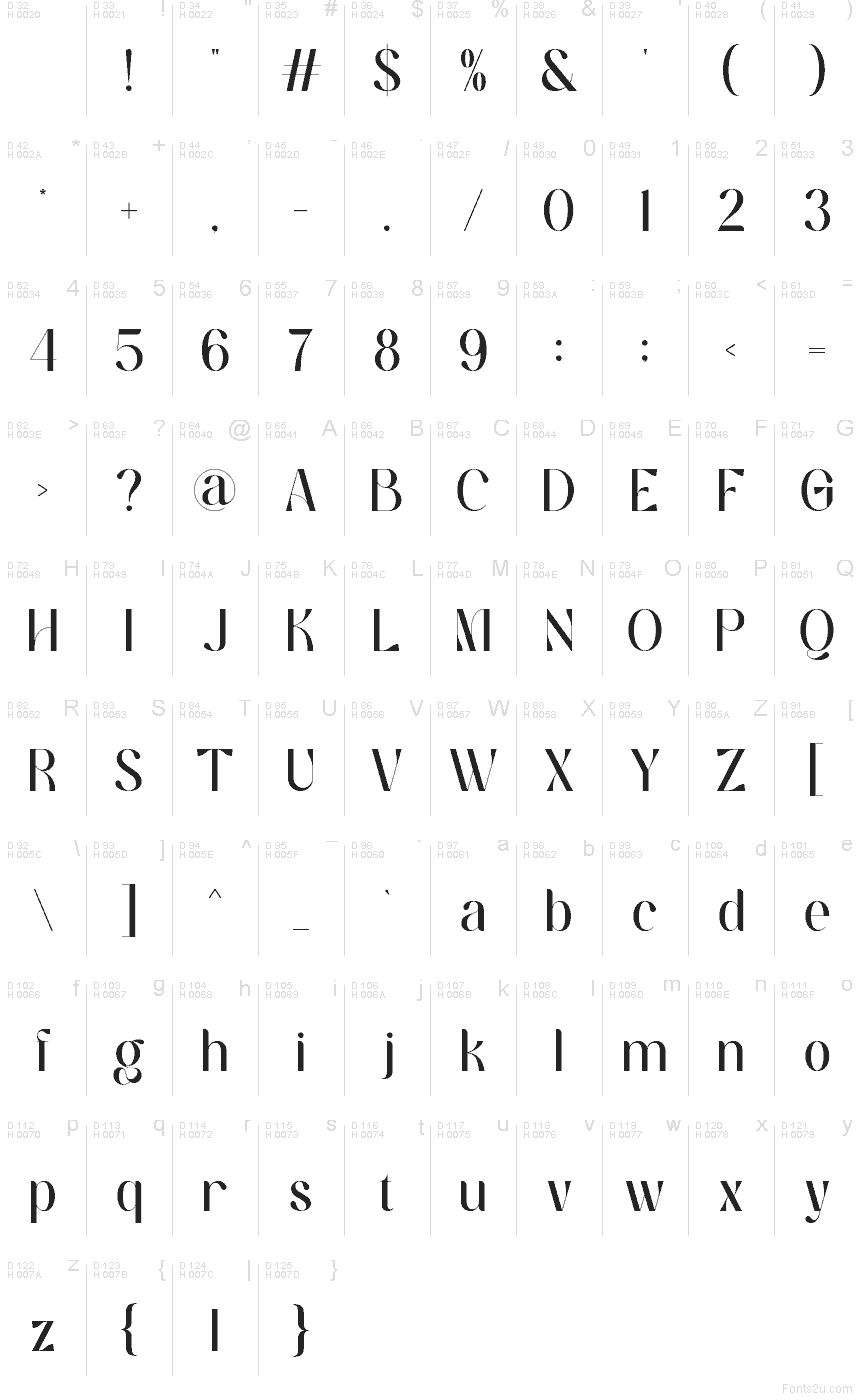
Bugate to darmowy krój szeryfowy od Ermedia Studio, wyróżniający się wyważonymi krzywiznami i nowoczesnym, editorialowym charakterem. Rytm grubych i cienkich linii oraz zapętlona mała litera „g” nadają literom wyrafinowany, nieco teatralny charakter.
Ten darmowy font sprawdzi się w modowych nagłówkach, opakowaniach kosmetyków, na okładkach magazynów, etykietach perfum i w eleganckich tytułach. Wykorzystaj go tam, gdzie krótkie słowo lub nazwa pozwolą wybrzmieć jego dramatycznym krzywiznom i delikatnemu kontrastowi.